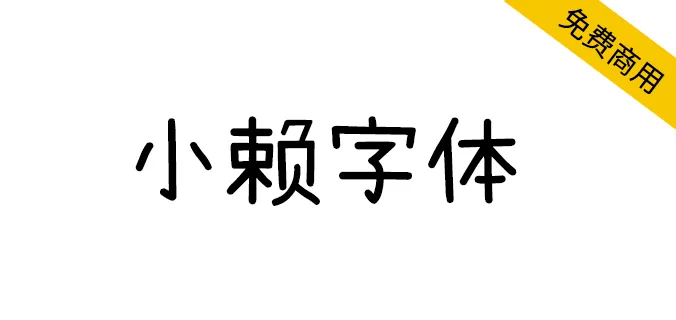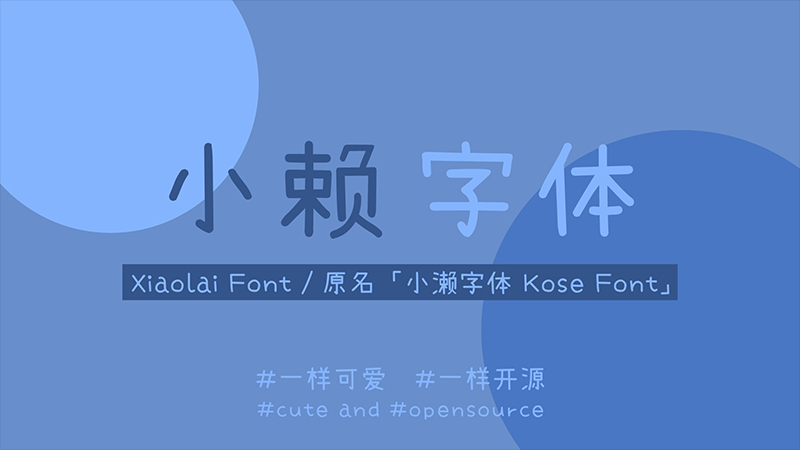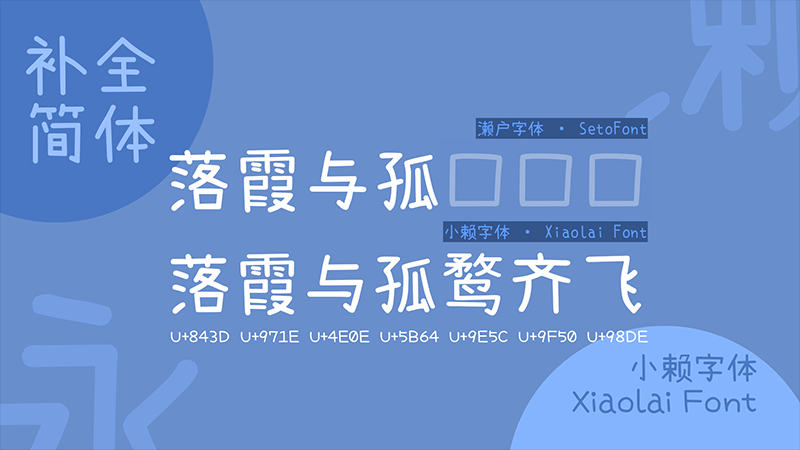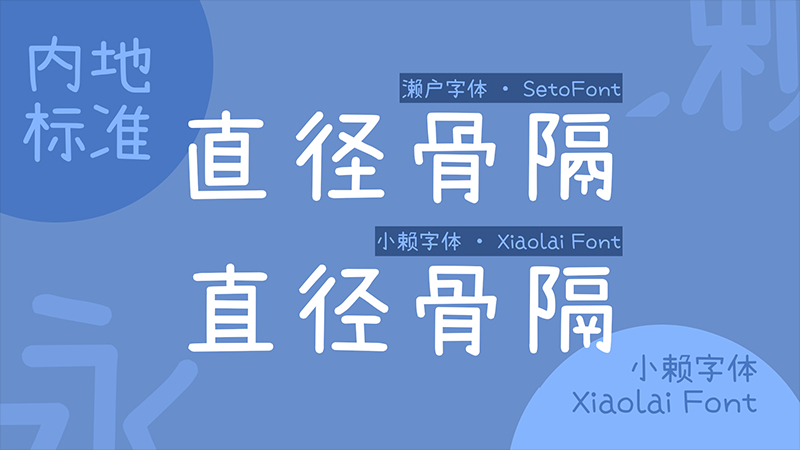
瀨戶字體 是由日本的業餘字體設計師 瀬戸のぞみ 製作,支持 JIS 第一至第四級,支持繁體和簡體中文(部分)。目前最新的版本是 2014 年 9 月 24 日的 6.20 版本,原作者已經很久不更新了。
後來,Max 在原來的「瀨戶字體」基礎上,推出了 內海字體 ,補齊了臺灣教育部門列出的 4808 個常用字,並增加了閩南語、粵語常用字,彌補了繁體中文地區常用字缺字缺憾。
但是,這款可愛的開源字體,仍然缺少一部分簡體字,這對於大陸的用戶來說,可能會造成一些不便。
於是,本人開啟了 “瀨戶內海字體簡體補全計劃” ,旨在補足 瀨戶字體 和 內海字體 缺少的簡體字。 小賴字體 是這一計劃的延續。
本字體項目原名為 「小瀨字體」 ,後來由於很多人都把「瀨」打成「賴」,索性把「氵」去掉,改名 「小賴字體」 。
本字體是 瀨戶字體 / 內海字體 的簡體中文化改良,利用瀨戶/內海字體裡原有的部件,對原字體中缺少的漢字進行補足,該字體可顯示 GB18030-2000 範圍內的全部漢字(共 27484 個),以及《通用規範漢字表》裡的全部漢字(共 8105 個),滿足中國大陸用戶的使用需要。此外可顯示日文假名、諺文 (韓文、朝鮮文) 音節和思源黑體可以顯示的特殊符號,可直接用作手機字體。
此外新增日本寫法的字體,保留「瀨戶字體」原汁原味的日系風格。日本版保留原 「小瀨字體(Kosefont-JP)」 名稱